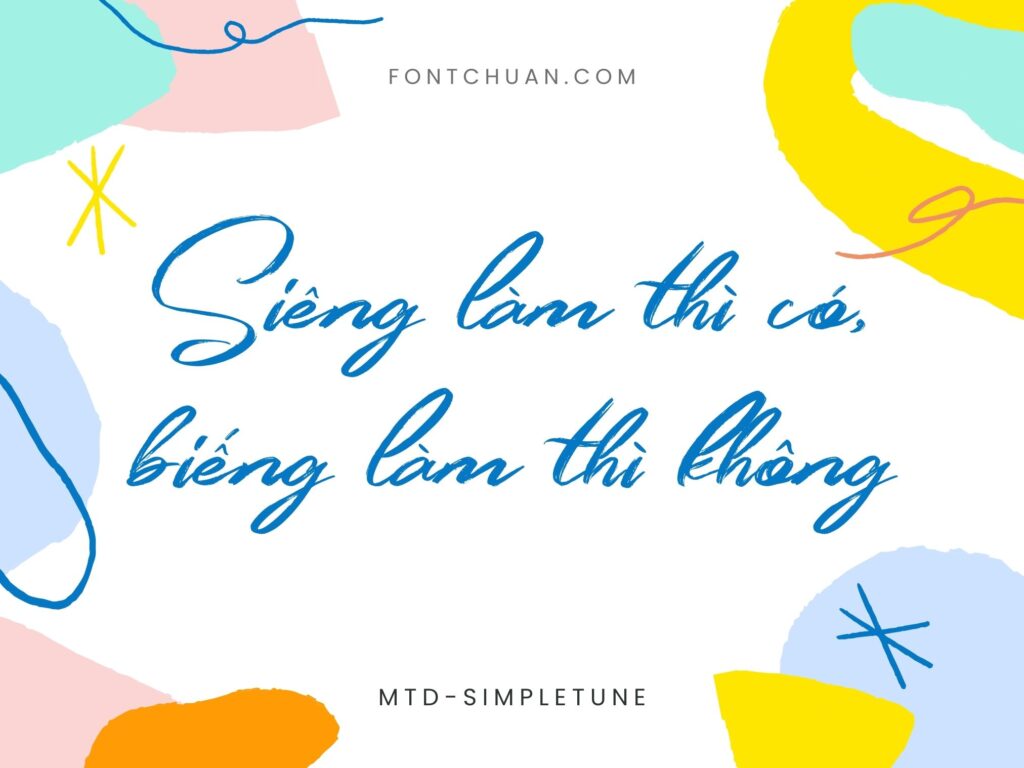
Font MTD Simpletune Việt Hóa
Font MTD Simpletune là một kiểu chữ viết tay hiện đại với nét chữ mềm mại và uyển chuyển, mang đến cảm giác thân thiện và gần gũi. Được Việt hóa bởi Mộc Hạ, font này hỗ trợ đầy đủ tiếng Việt cùng hơn 90 ngôn ngữ khác, mở rộng khả năng ứng dụng trong các thiết kế đa ngôn ngữ. Đây là một trong những phông chữ được cộng đồng thiết kế đánh giá cao và sử dụng trong nhiều dự án sáng tạo, đáp ứng nhu cầu đa dạng của người dùng.
MTD Simpletune nổi bật với phong cách viết tay tự nhiên và thanh lịch, rất phù hợp cho các thiết kế logo, tiêu đề, bao bì sản phẩm, thiệp mời và các ấn phẩm đòi hỏi sự sáng tạo và cá nhân hóa. Các ngành nghề phù hợp bao gồm quảng cáo, giáo dục, công nghệ, thiệp cưới và ảnh cưới. Font này cũng lý tưởng cho các sự kiện như Tết, Giáng sinh, Valentine và các lễ hội khác.